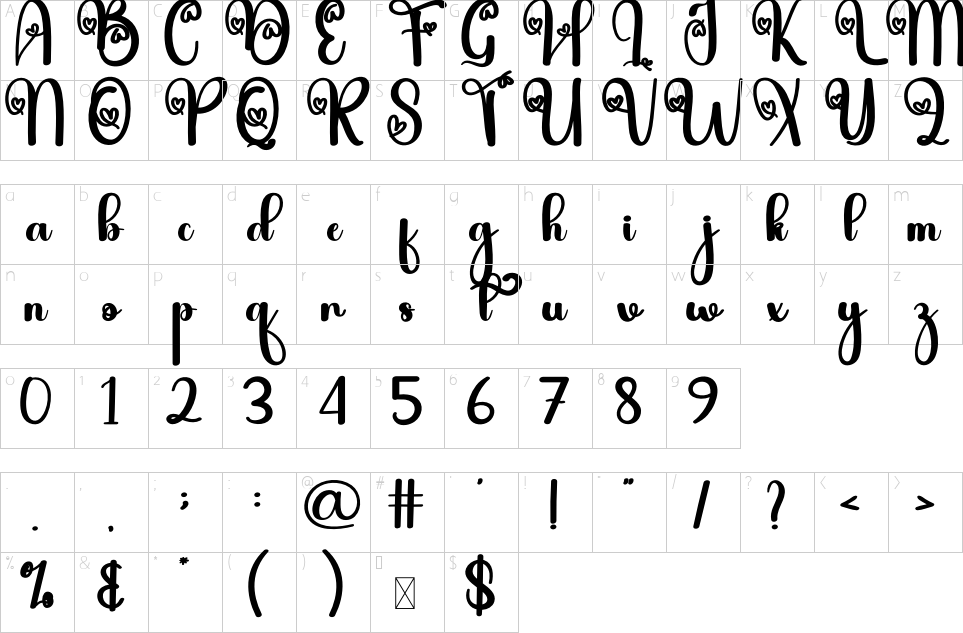
Daddy Handsome Font – Download Grátis
Descubra Daddy Handsome, uma nova fonte que se destaca pela sua elegância e sofisticação. Desenhada por William Jhordy, esta tipografia oferece um toque irresistivelmente atraente para gráficos digitais. Se você está procurando por uma fonte para adicionar um charme especial aos seus projetos, Daddy Handsome é uma escolha perfeita. Com sua designação atenciosa e elegante, ela se destaca em qualquer ambiente de texto, desde o contraste moderno até os detalhes mais delicados. As pessoas que desejam incorporar uma personalidade única em suas criações agora podem fazê-lo com Daddy Handsome, uma fonte gratuita disponível tanto para Windows quanto para Mac. Com apenas 1. 136 downloads, já se pode sentir a energia de quem confia nesta fonte, pronta para transformar qualquer projeto em um verdadeiro trabalho de arte. Descubra a diferença que Daddy Handsome faz e reviva sua paleta de criações digitais!